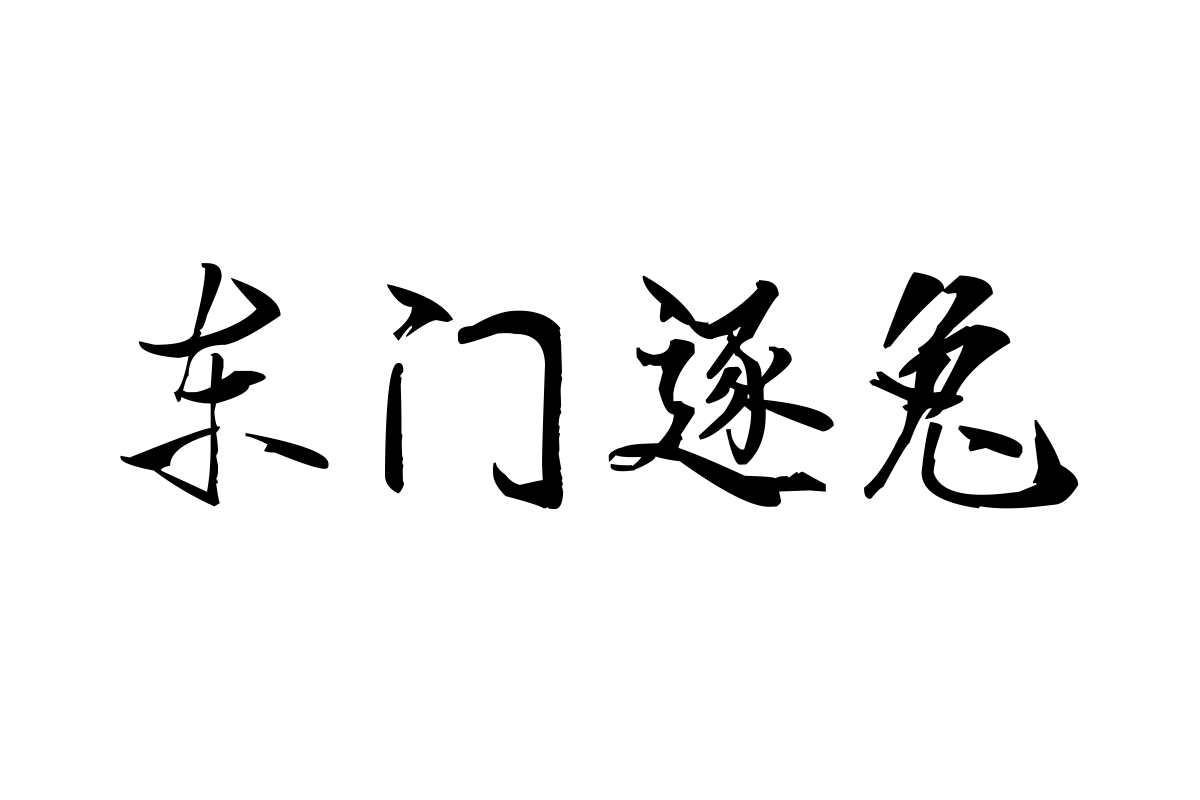
汉标老梁行楷是一套具有独特风格的中文字体,由著名书法家汉标设计。这套字体以其流畅的线条和独特的结构而著称,给人一种优雅而古朴的感觉。
汉标老梁行楷的笔画粗细适中,线条流畅自然,给人一种轻松愉悦的感觉。每个字的笔画都经过了精心设计,使得整个字体看起来既美观又大方。此外,这套字体还注重平衡和对称感,使得整体效果更加和谐统一。
汉标老梁行楷的字形结构独特,每个字都有自己独特的形状和结构。这使得整套字体在视觉上具有很强的辨识度和美感。同时,由于每个字的形状和结构都有所不同,这也使得整套字体在使用时能够更好地适应各种场景和需求。
总的来说,汉标老梁行楷是一款非常优秀的中文字体,无论是用于正式场合还是用于创意设计,都能展现出其独特的魅力和风格。